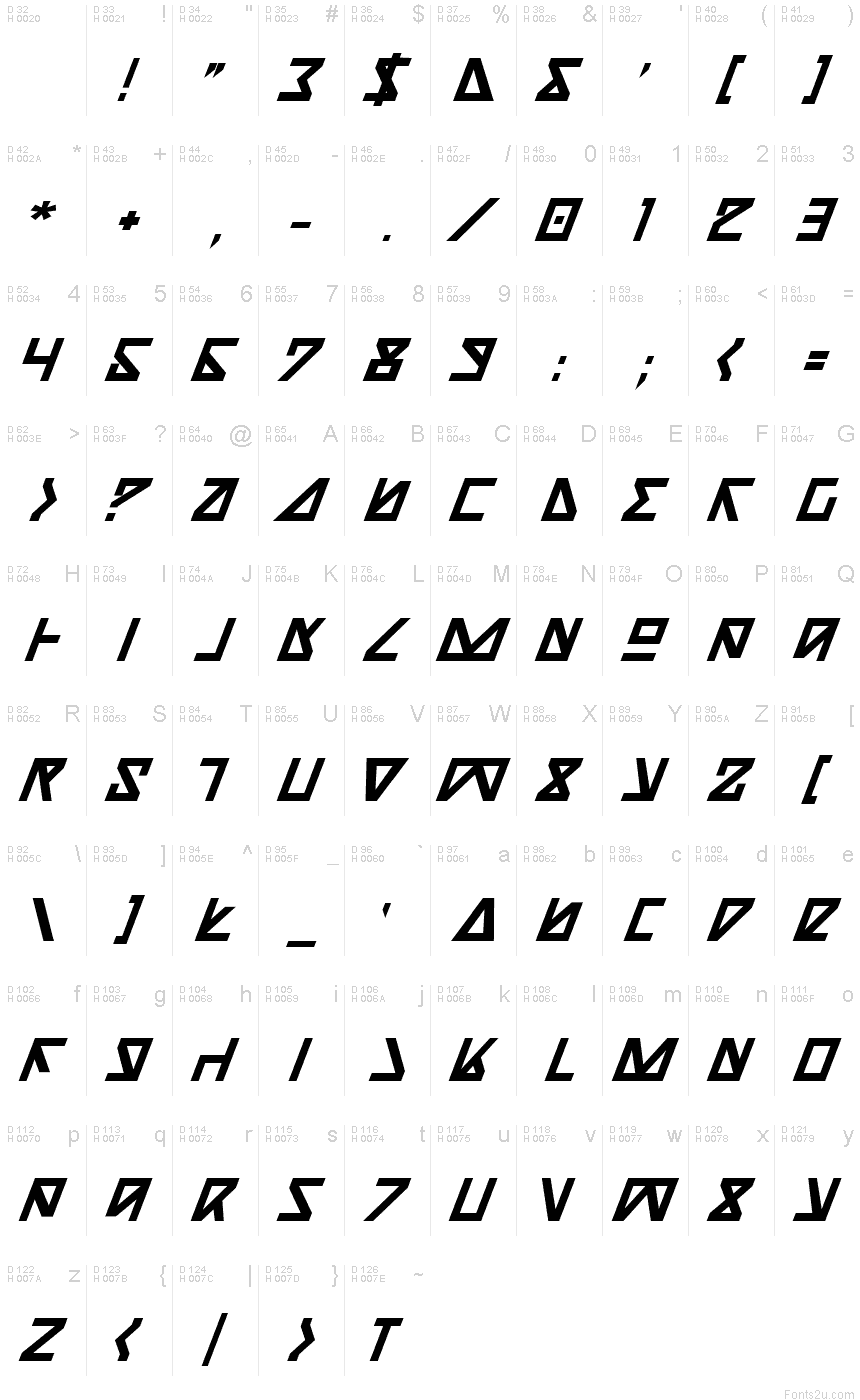
Nick Turbo Bold Italic od Iconian Fonts to darmowy krój display w stylu techno. Jego szybka, nachylona do przodu sylwetka i ostre cięcia diagonalne sprawiają, że litery wyglądają, jakby przecinały przestrzeń. Powtarzające się formy klinów i wąskie odstępy nadają projektowi wyrazisty, inżynieryjny rytm, daleki od generycznego, sci-fi wykończenia.
Świetnie sprawdzi się w tytułach gier, grafikach esportowych, nagłówkach plakatów, okładkach albumów i nakładkach streamingowych, gdzie ukośna geometria wykonuje większość wizualnej pracy. Krótkie napisy i logotypy również zyskują dzięki wyciętym formom, które tworzą wrażenie prędkości i mechaniki bez potrzeby stosowania dodatkowych efektów.
Nick Turbo Bold Italic